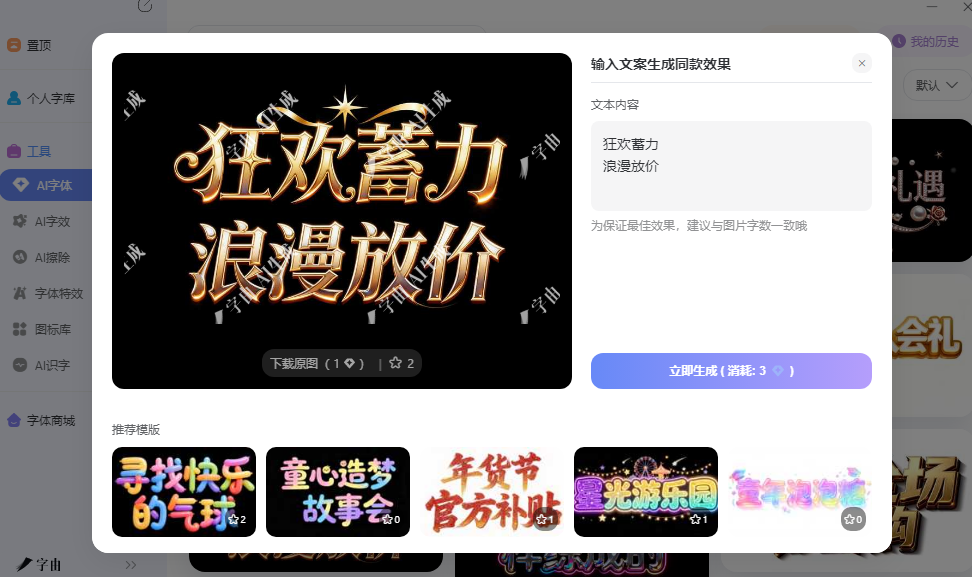
想要立体字标题?艺术字在线生成器一键搞定
做海报或者PPT封面时,立体字标题的视觉冲击力比普通平面字体强很多。文字带有厚度感和光影层次,一眼就能抓住注意力。但做出这种效果通常要打开C4D或者Blender建模,再导入PS调材质,整个过程耗时很长,对不会三维软件的人来说门槛太高。其实有不少艺术字在线生成器可以直接生成立体字图片,输入文案就能拿到带厚度感的PNG素材,直接插进设计稿里用。
字由的AI字效里有专门的立体和3D模板分类。这些模板模拟了真实的厚度感和材质反光,金属质感会让文字侧面呈现出镜面反射,玻璃质感会让文字带有通透的折射效果,霓虹管模板则模拟了发光灯管在暗夜中的散射光晕。透明背景意味着可以直接叠加在各种底图上。做PPT时插入到幻灯片里,文字悬浮在背景图片上方,不会留下白色方块。做电商详情页时拖进商品图上方,立体标题和商品形成前后层次。做活动海报时叠加在渐变背景上,立体字的厚度边缘会自然承接背景色的变化,融合度比较高。
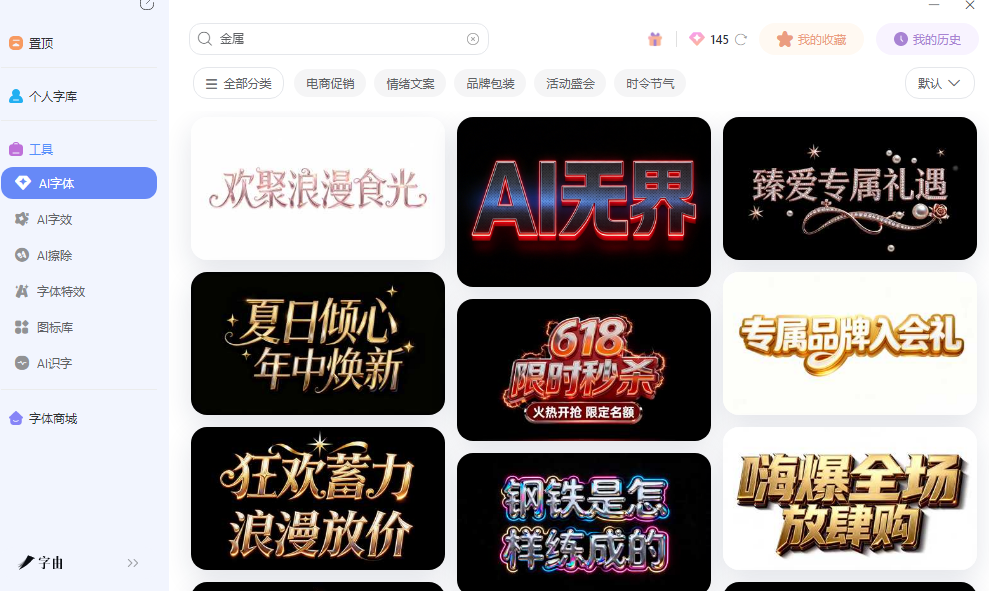
PPT里插入立体字图片后,可以配合动画效果使用。比如给立体字添加浮入动画,文字逐层显现的过程和立体厚度结合,在汇报演示时视觉层次感比较明显。字由生成的PNG分辨率足够应付投影显示,放大后边缘清晰度保持得不错。
2、Online Fonts Generator
Online Fonts Generator是一个在线字体风格转换工具,属于艺术字在线生成器的一种。输入文字后,系统会转换为多种艺术化样式,包括草书、哥特体、涂鸦体、复古印刷体等。每种样式都支持实时预览,用户可以输入自己的文案后并排对比不同风格的效果,快速找到最匹配项目气质的那一款。
这个工具对需要批量浏览和对比不同艺术字风格的用户比较友好。作为艺术字在线生成器,它的优势在于风格跨度大,从古典到现代都有覆盖,且支持实时并排对比,省去了逐个试的麻烦。生成的结果可以复制为文本,也可以下载为图片,输出方式比较灵活。对于做品牌方案时需要快速出多个风格方向给客户确认的场景,这里的对比功能比较实用。
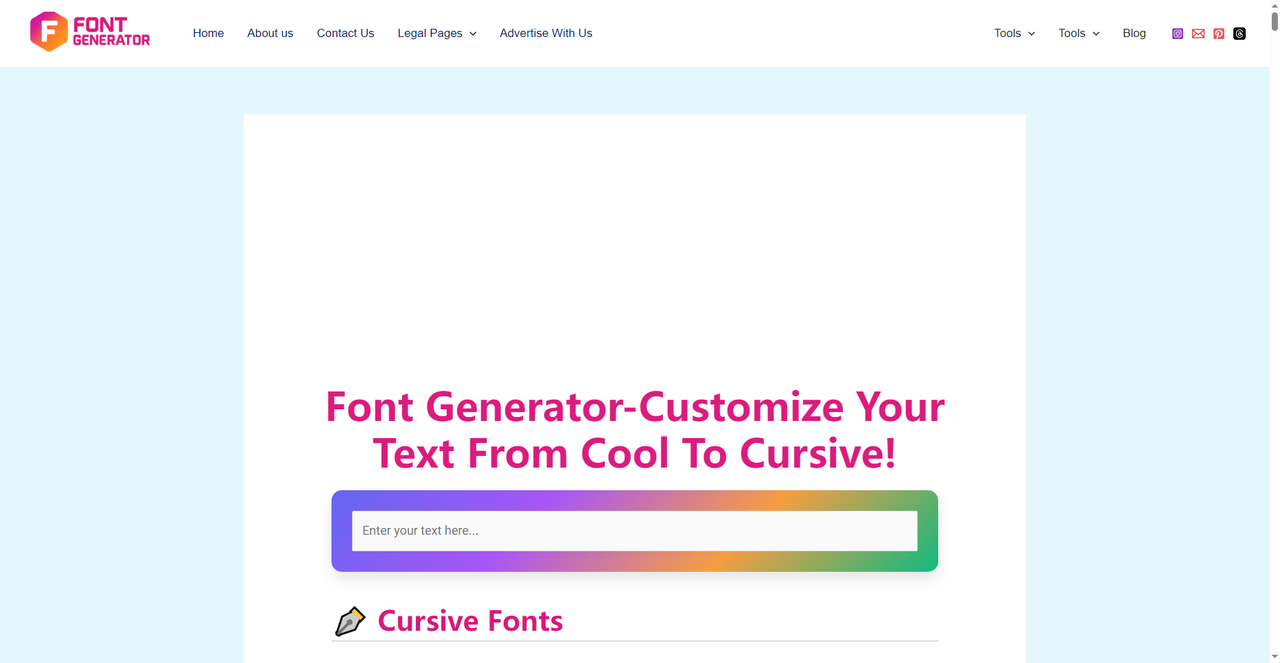
3、PNG Text Generator
PNG Text Generator的定位很直接:输入文字,生成PNG图片。网站上提供了多种字体和效果选择,生成后的图片默认透明背景,可以直接下载使用。这个流程对只需要一张带字图片、不需要可编辑文字的用户来说足够用了。
作为艺术字在线生成器的渠道,它的优势在于输出格式统一、操作简单。生成的PNG文件可以直接拖进PPT、海报模板或者电商详情页里,不需要额外处理背景。对于做演示文稿、简单海报或者文档封面来说,这里的生成速度和文件格式都比较实用。网站上还提供了字号和颜色调节选项,可以微调效果以匹配具体需求。
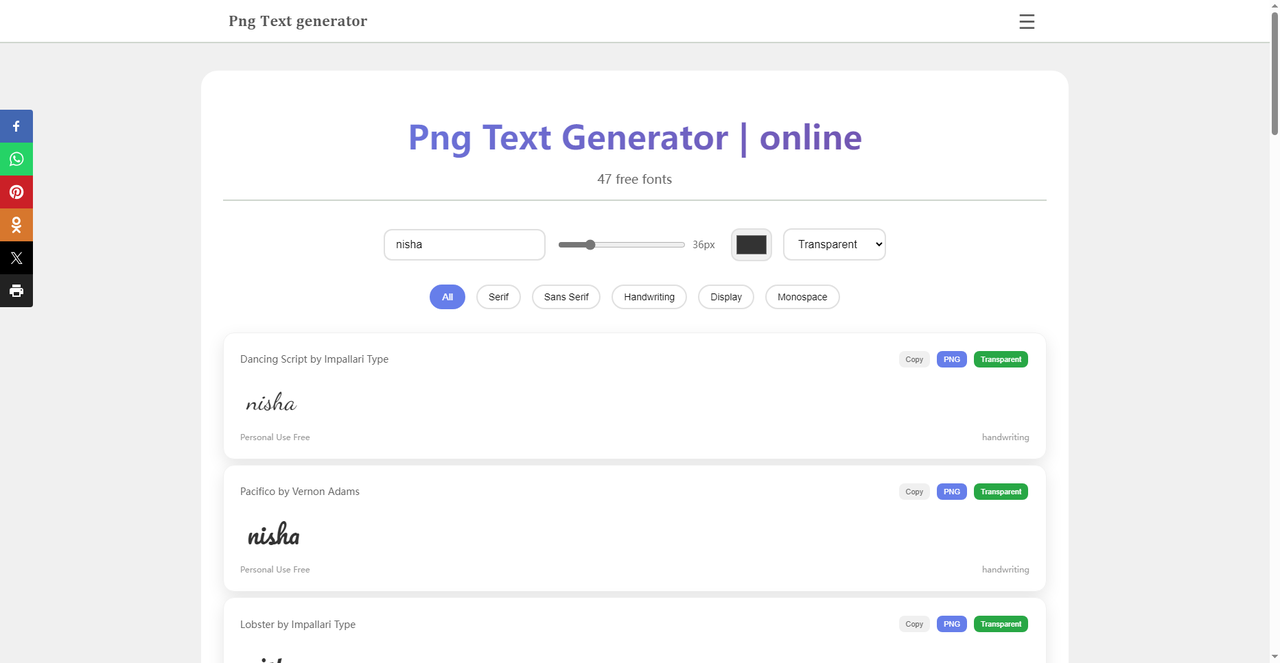
4、TextTrick
TextTrick专注花哨文字效果生成,是一个艺术字在线生成器。输入文字后,系统会应用多种装饰处理,包括阴影叠加、多重描边、渐变填充、立体浮雕等。这些效果可以组合使用,创造出比较复杂的视觉样式。用户可以在左侧的效果面板里逐项开启或关闭,实时看到预览。
这个工具对喜欢自己调配效果的用户比较实用。和套用固定模板不同,TextTrick允许逐项调整参数,但界面比专业设计软件简单得多。作为艺术字在线生成器,它的优势在于自由度高,可以做出比较个性化的效果。生成的结果可以复制为Unicode文本,也可以下载为图片格式,两种输出方式都支持,使用场景比较灵活。
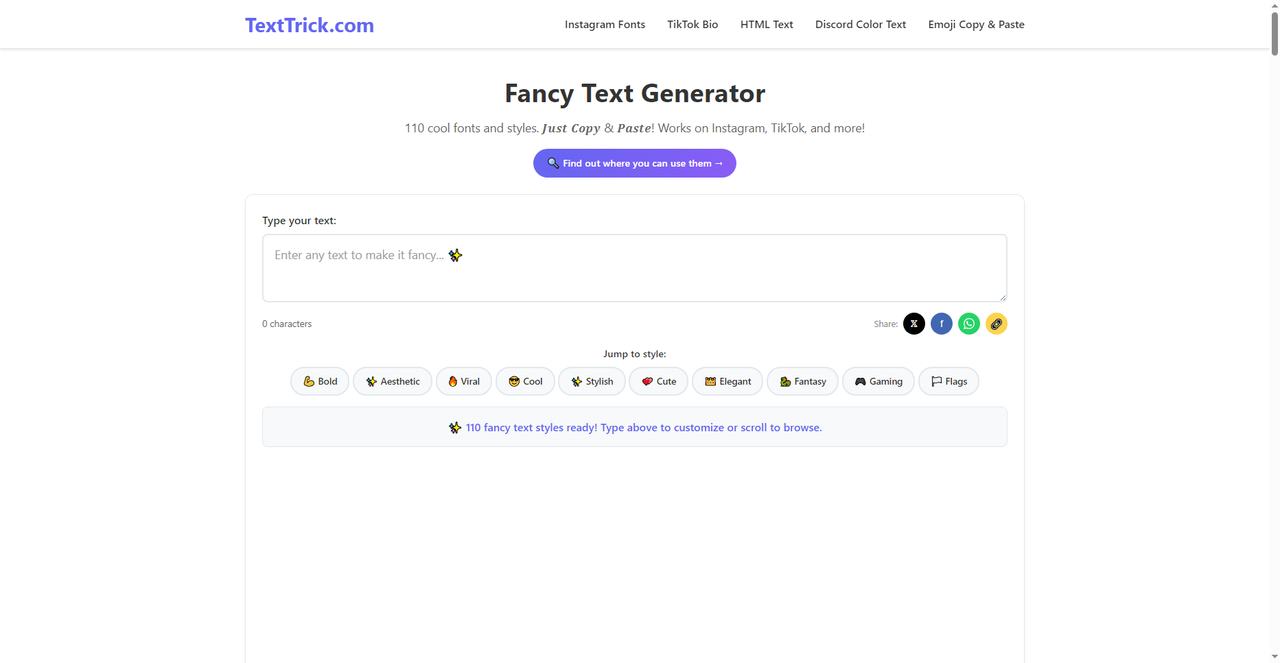
5、FontGen
FontGen是一个艺术字在线生成器,输入文字后会转换为多种Unicode装饰字符。这些字符不是图片,而是可以直接复制粘贴的文本格式,在社交媒体、聊天软件或者任何支持Unicode的平台上都能正常显示。风格包括花体、粗体、手写体、泡泡字等多种变体,点击即可切换。
这个工具对需要快速发一条带装饰性文字的朋友圈或者微博的用户比较友好。不需要生成图片文件,直接复制特殊字符粘贴到发布框里就能用,后续想改文字内容直接编辑即可。作为艺术字在线生成器的渠道,FontGen的优势在于输出格式灵活,不依赖图片,适合纯文本场景。网站上还提供了多种预设风格,不需要手动调参数,操作流程简洁。
FontGen生成的特殊字符在Instagram、Twitter、Facebook等主流社交平台上都能正常显示,不会被平台自动转换为普通字体。这个兼容性对新媒体运营者比较重要,有些工具生成的装饰字符在特定平台上会显示为方框或者乱码,FontGen的字符集覆盖面比较广,出现这种问题的概率比较低。
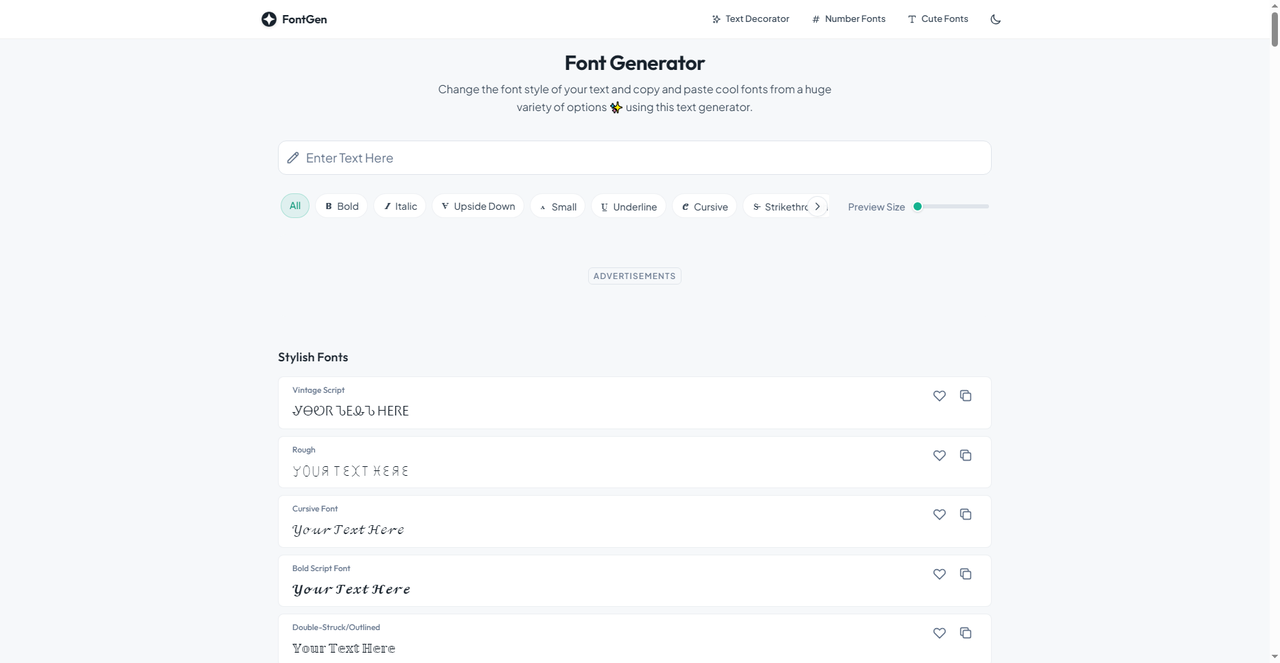
字由的AI字效几分钟就能出图,透明背景PNG直接插进PPT或者海报,配合每日免费额度,日常做几张标题完全够用。FontGen输出的是Unicode字符,直接复制到社交媒体发布框里就能用,不需要保存图片文件。TextTrick支持多层效果叠加,自由度比较高,适合想自己调配细节的人。PNG Text Generator专门出PNG素材,下载后拖进设计稿直接用。Online Fonts Generator可以并排对比多种风格,批量浏览时效率不错。